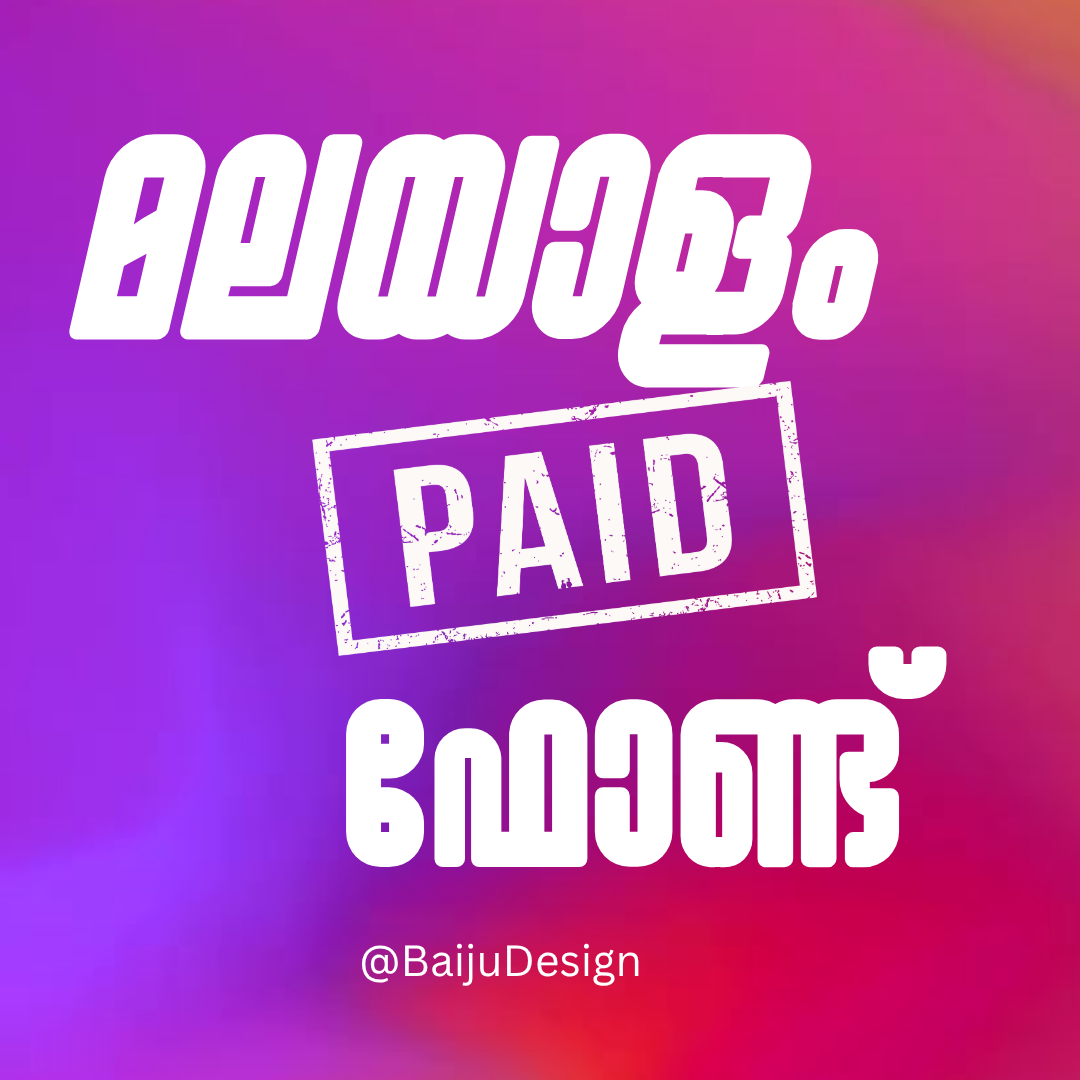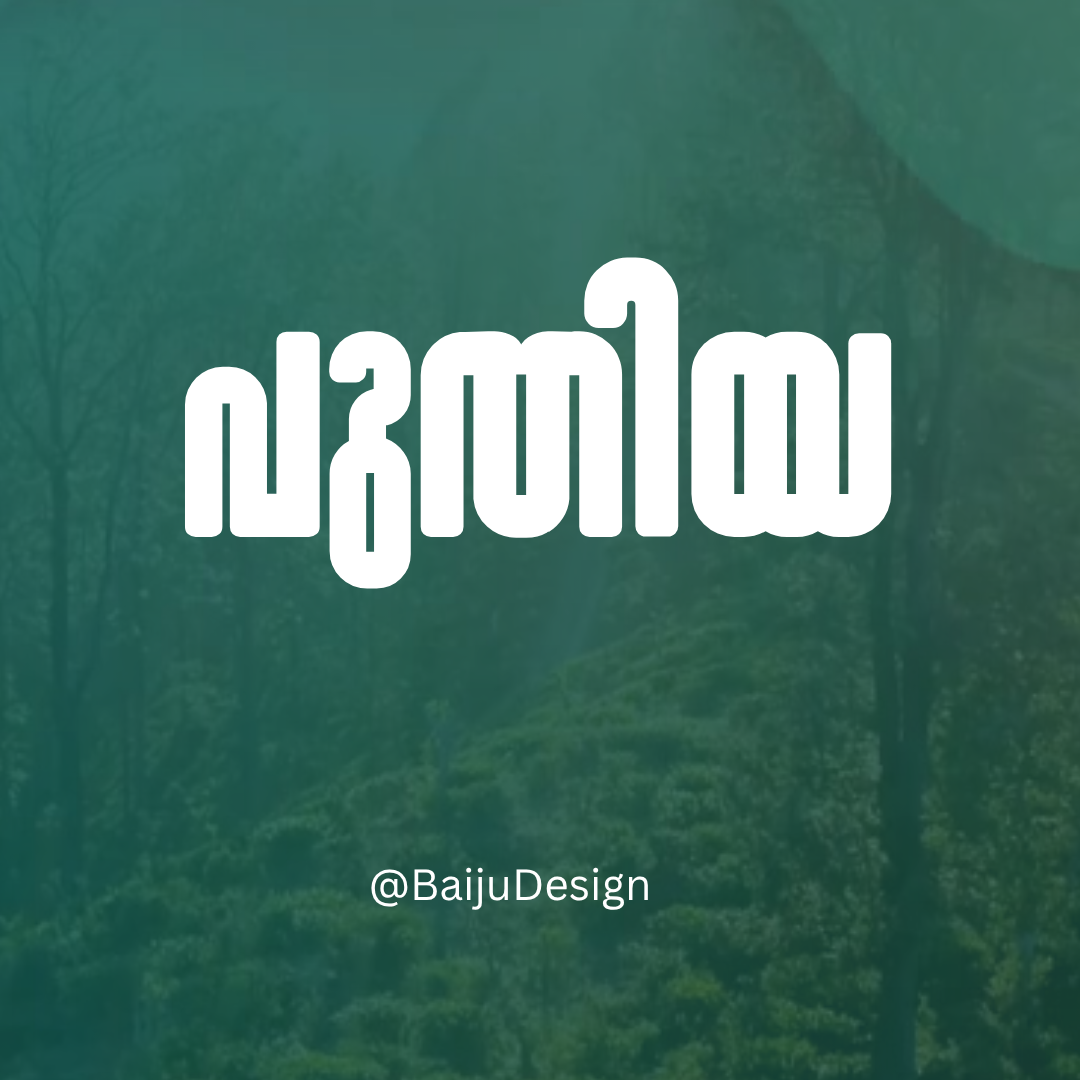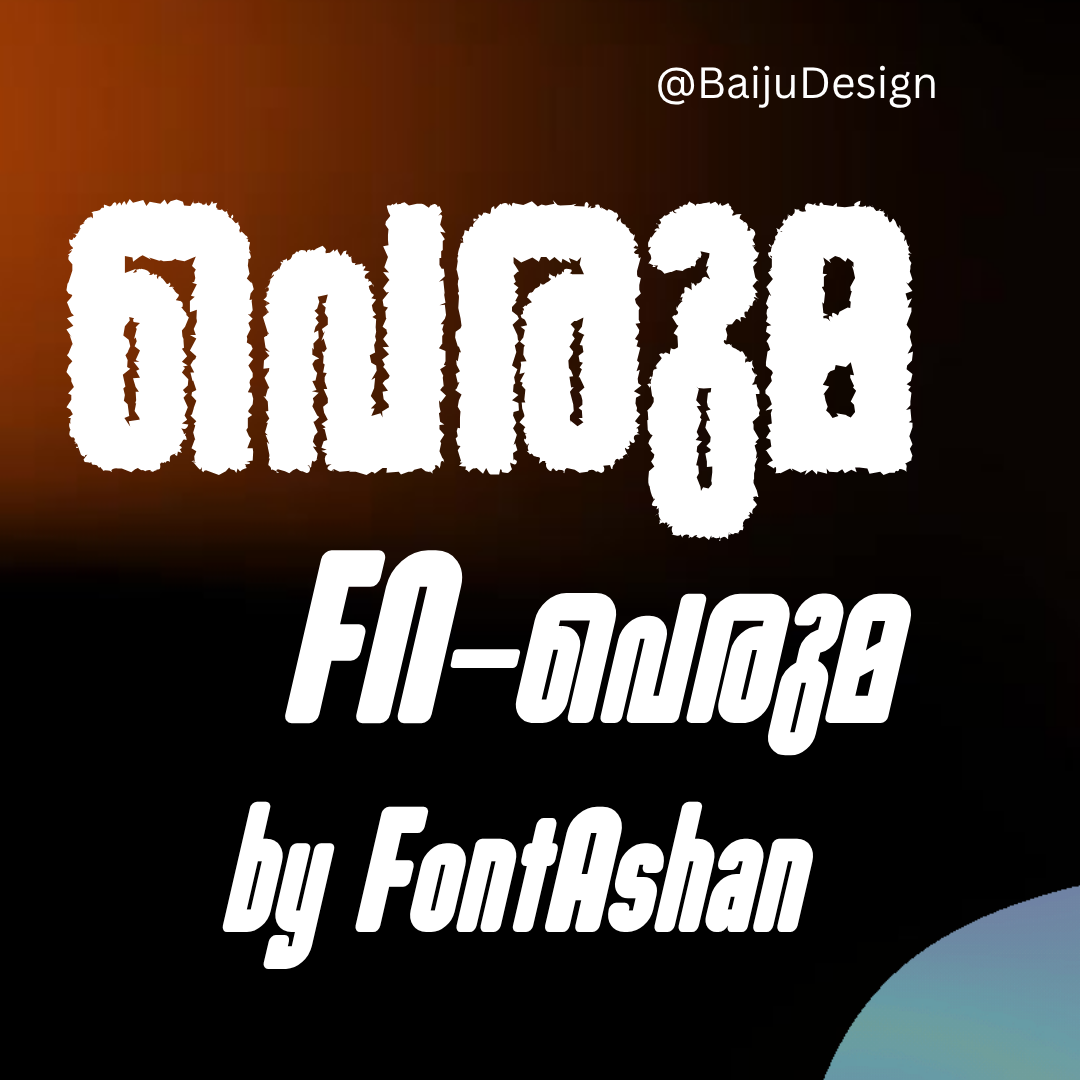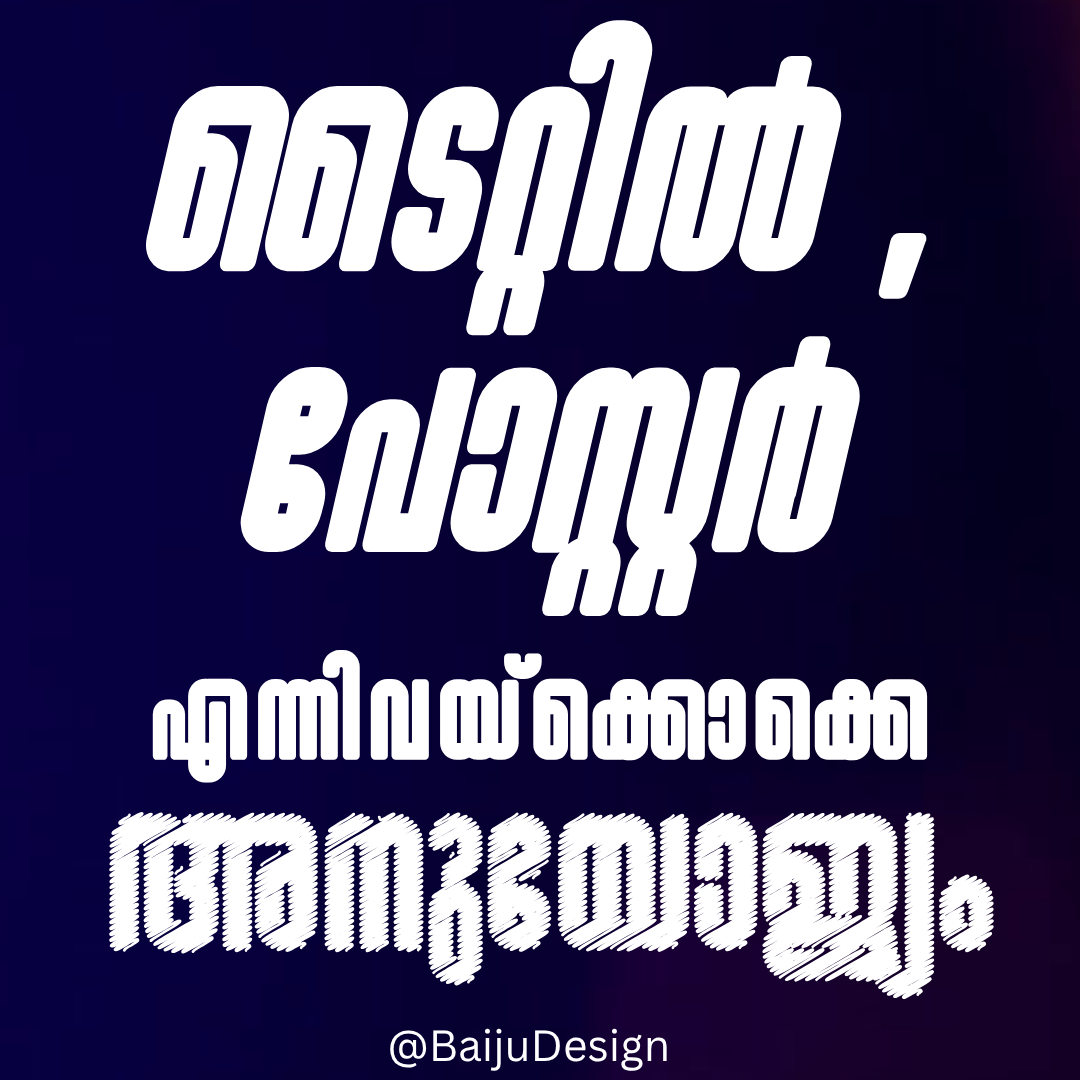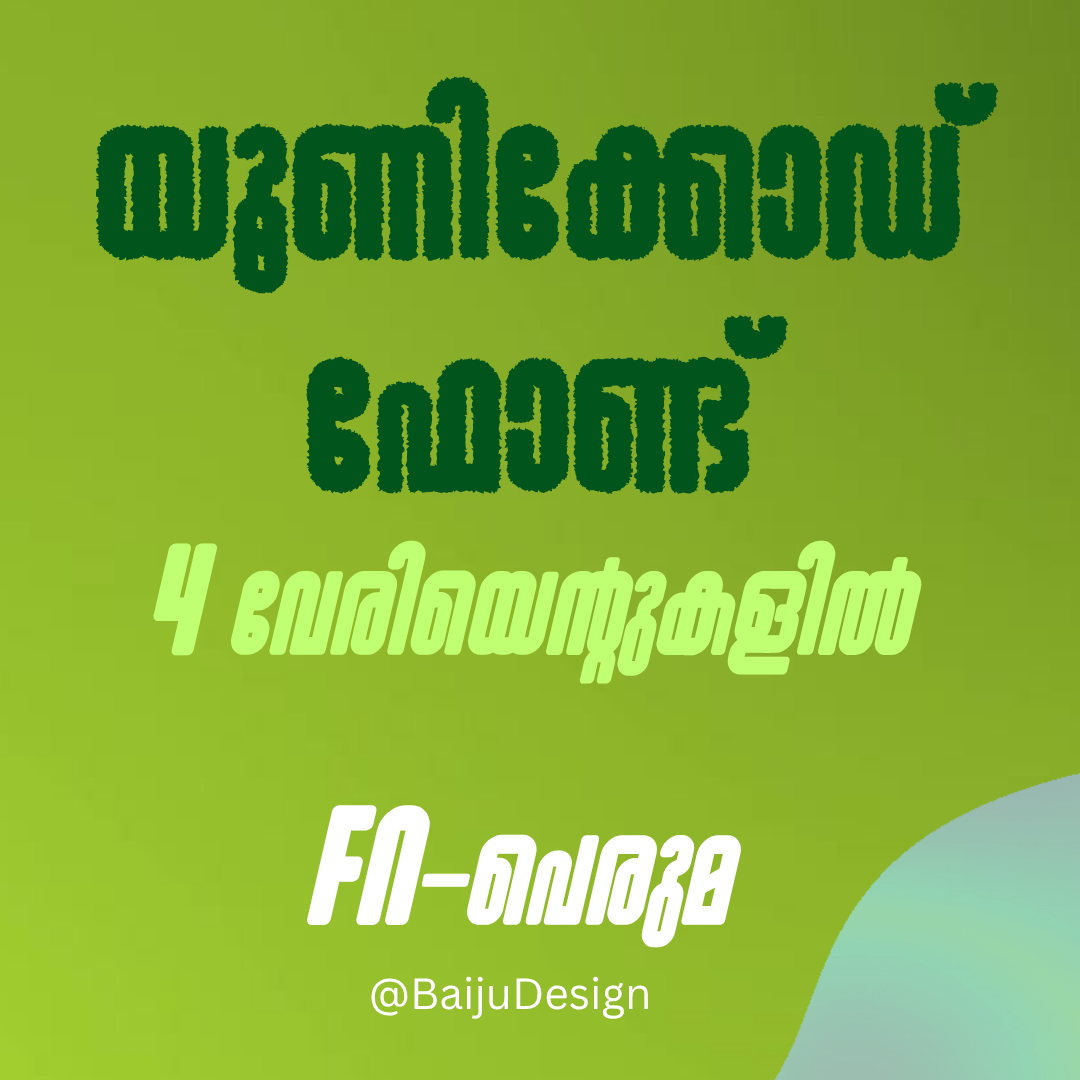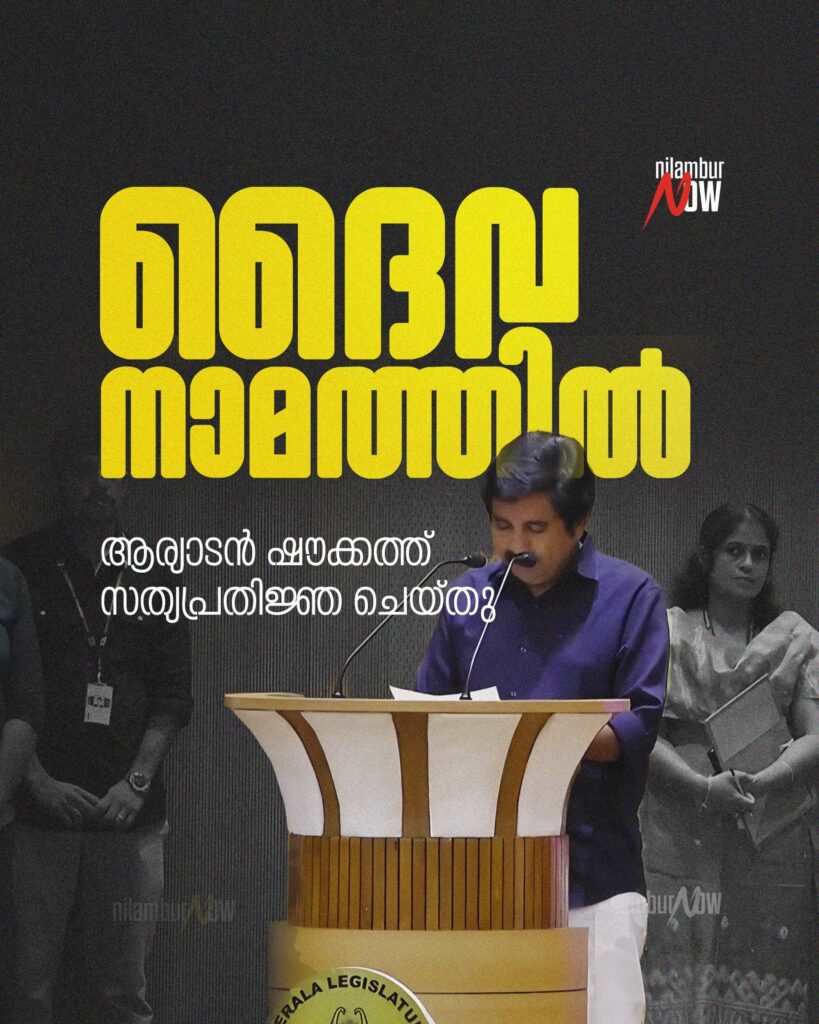
Malayalam Unicode, FN-Peruma
Premium Malayalam Font FN-Peruma
FN-Peruma യുടെ പ്രധാന സവിശേഷതകൾ:ദ്വിഭാഷാ മികവ്: മലയാളത്തിലും ഇംഗ്ലീഷിലും ഒരുപോലെ ആകർഷകമായി ഉപയോഗിക്കാൻ കഴിയുന്ന യൂണിക്കോഡ് ഫോണ്ട്.
നിങ്ങളുടെ ഡിസൈനുകളിൽ ഭാഷകൾക്കിടയിൽ തടസ്സമില്ലാത്ത ഒഴുക്ക് ഇത് നൽകുന്നു.ട്രെൻഡി ഡിസ്പ്ലേ സാൻസ് സെരിഫ്: പുതിയ ട്രെൻഡ് ലുക്കിലുള്ള ഡിസ്പ്ലേ സാൻസ് സെരിഫ് ഫോണ്ടാണിത്.
ഏതൊരു വിഷ്വൽ പ്രോജക്റ്റിലും ശക്തമായ ഒരു സ്റ്റേറ്റ്മെന്റ് നൽകാൻ ഇത് സഹായിക്കുന്നു.
ശക്തവും വൈവിധ്യപൂർണ്ണവും: നിങ്ങളുടെ ആശയങ്ങൾക്ക് കരുത്ത് പകരുന്ന ഈ ഫോണ്ട് താഴെ പറയുന്നവയ്ക്ക് ഏറ്റവും അനുയോജ്യമാണ്:
ലോഗോകൾ: ഓർമ്മിക്കപ്പെടുന്നതും അതുല്യവുമായ ബ്രാൻഡ് ഐഡന്റിറ്റികൾ സൃഷ്ടിക്കാൻ.പോസ്റ്റർ ടൈറ്റിലുകൾ: ശ്രദ്ധ പിടിച്ചുപറ്റുന്ന തലക്കെട്ടുകൾക്ക്.മുവി ടൈറ്റിലുകൾ: സിനിമയുടെ തനിമയും ഗാംഭീര്യവും വിളിച്ചോതുന്ന തലക്കെട്ടുകൾക്ക്.മാഗസിൻ കവറുകൾ: വായനക്കാരെ ആകർഷിക്കുന്ന കവറുകൾക്ക്.ബുക്ക് ടൈറ്റിലുകൾ: ആകർഷകമായതും ശക്തവുമായ ടൈപ്പോഗ്രഫിയിലൂടെ വായനക്കാരെ സ്വാധീനിക്കാൻ.
മൊബൈൽ ഫ്രണ്ട്ലി: എല്ലാ സ്ക്രീൻ വലുപ്പങ്ങൾക്കും അനുയോജ്യമായ രീതിയിൽ ഒപ്റ്റിമൈസ് ചെയ്തിരിക്കുന്നു, നിങ്ങളുടെ ഉള്ളടക്കം മൊബൈൽ ഉപകരണങ്ങളിൽ വ്യക്തവും പ്രൊഫഷണലുമായി കാണപ്പെടുന്നുവെന്ന് FN-Peruma ഉറപ്പാക്കുന്നു.
സമ്പൂർണ്ണ പതിപ്പുകൾ: ഇറ്റാലിക്, ബോൾഡ് വേർഷനുകൾ ലഭ്യമാണ്, ഇത് നിങ്ങൾക്ക് കൂടുതൽ ഡിസൈൻ സ്വാതന്ത്ര്യം നൽകുന്നു.
| Font Type | Display style font |
| Creator / Designer | Enmark Brands & FontAshan |
| Publisher | FONT ASHAN |